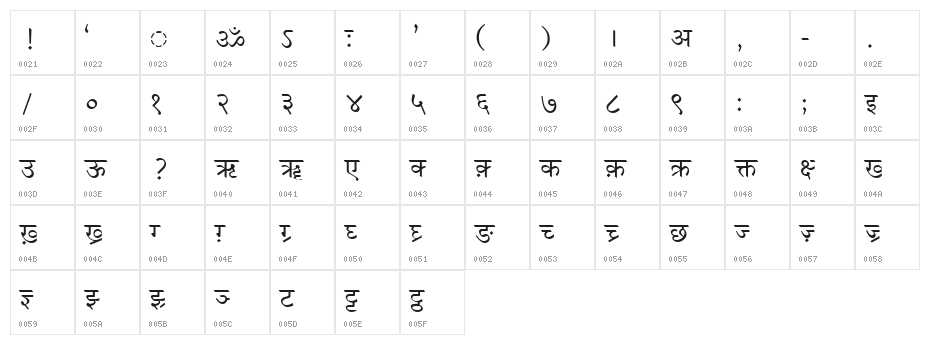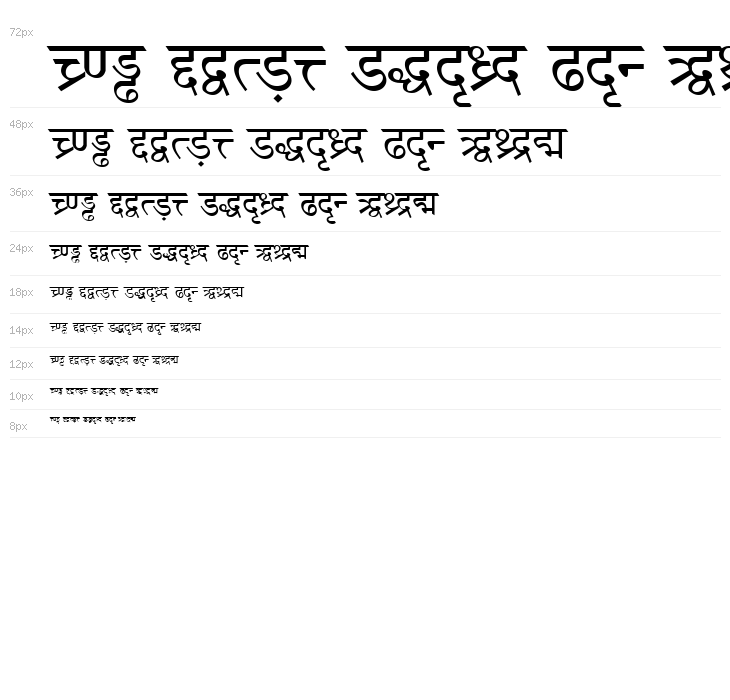
DV-TTSurekh Normal Font
| समग्र शैली | Classic |
| उपयोग का मामला | Body text, Educational materials, Cultural publications |
| सुझाए गए प्रोजेक्ट | Ideal for cultural publications, educational materials, and digital content that require a traditional yet clear Devanagari script. |